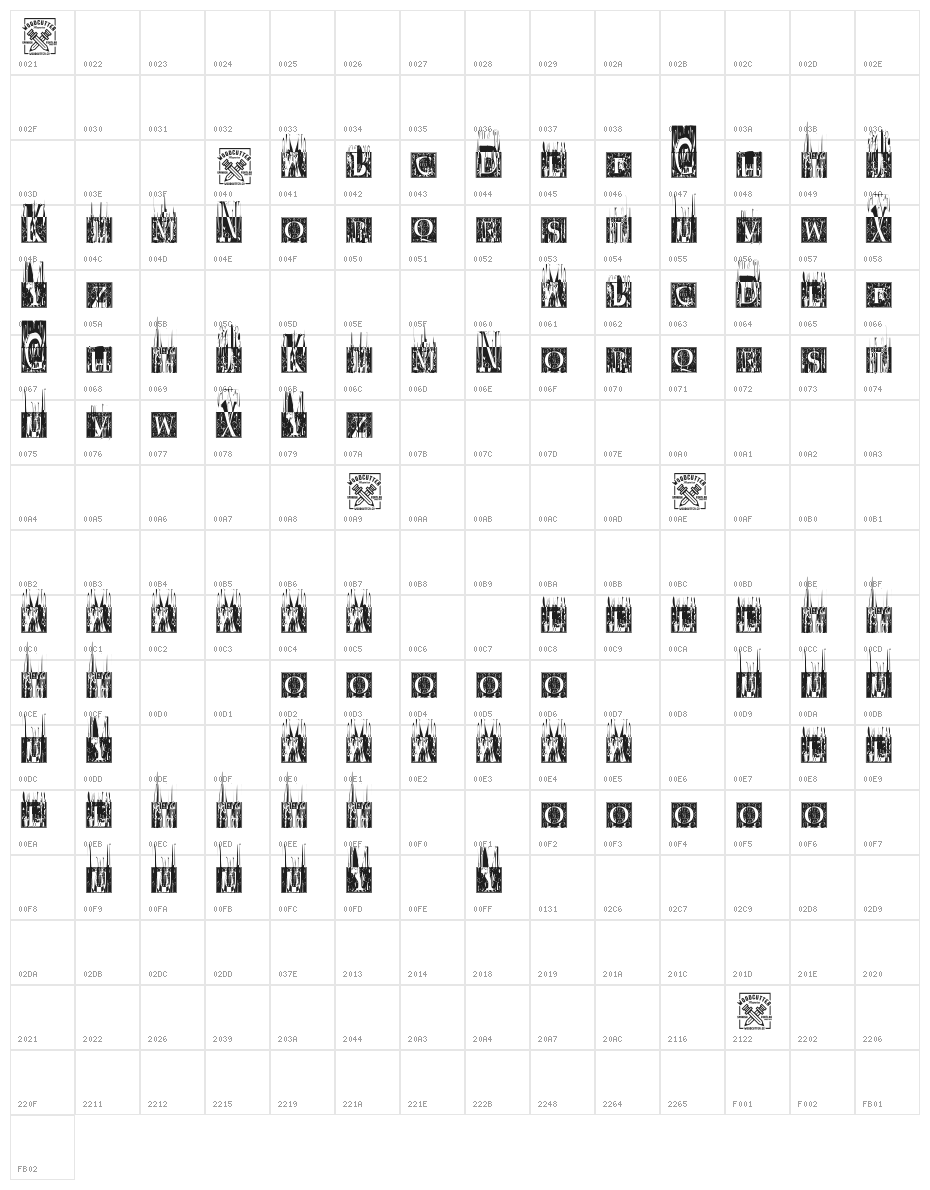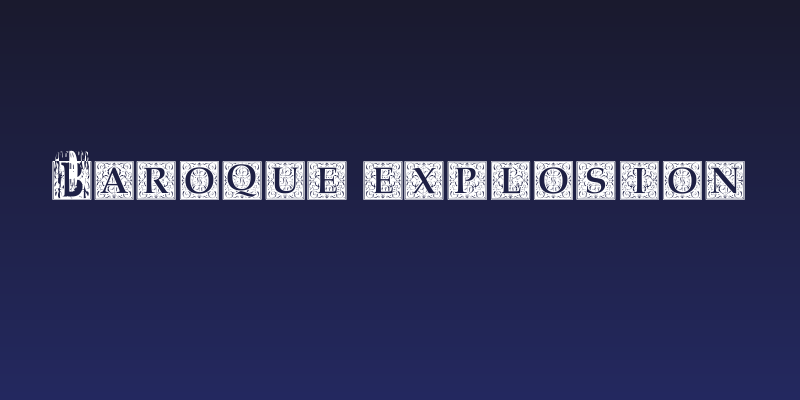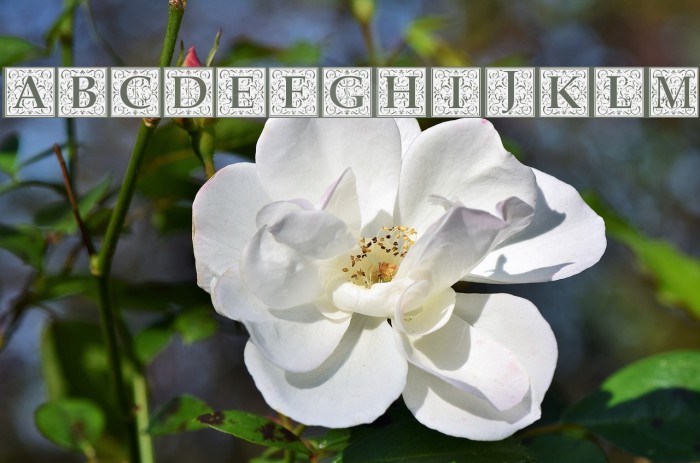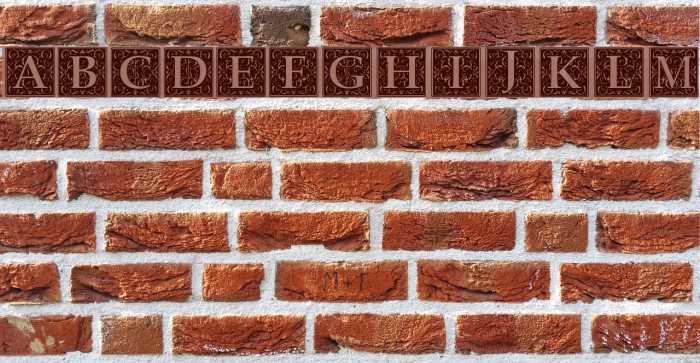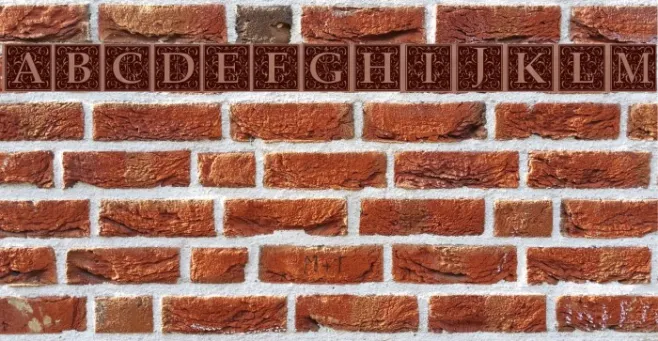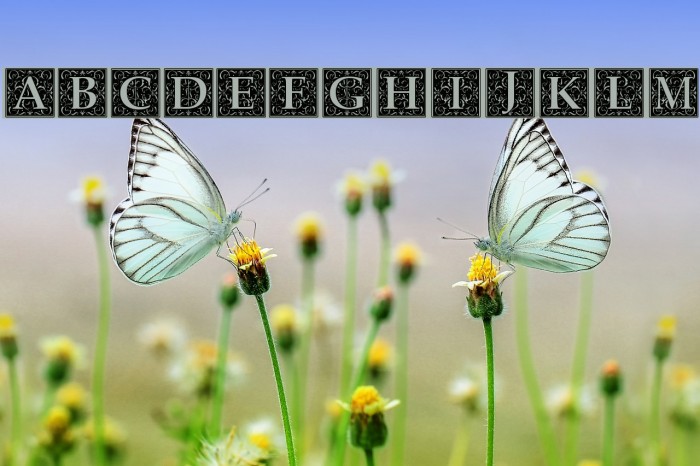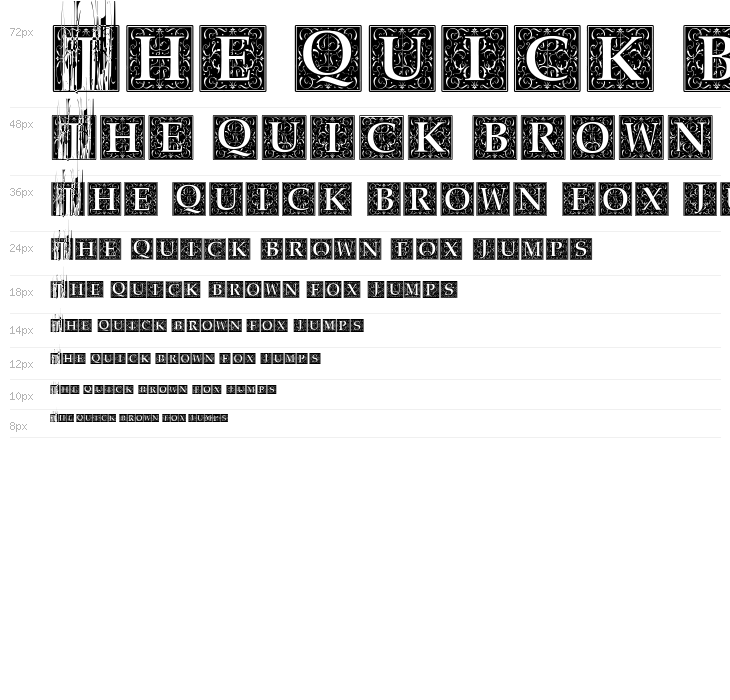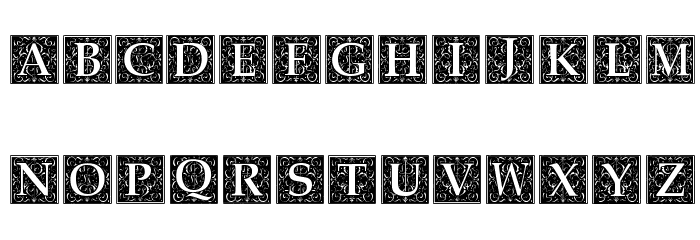
Baroque Explosion Font
| Estilo general | Vintage, Decorative |
| Proyectos propuestos | Ideal for wedding invitations, luxury branding, historical-themed posters, and decorative book covers. |